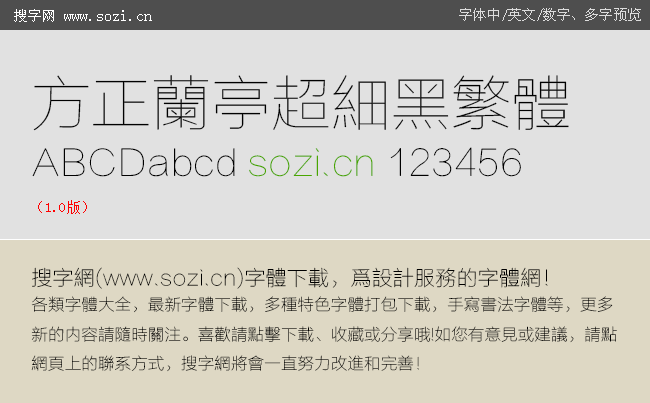
方正蘭亭超細(xì)黑繁體(FZLTCXHFW)
搜字網(wǎng)提供一款方正蘭亭超細(xì)黑繁體中文字體下載,方正蘭亭超細(xì)黑是一款線條非常細(xì)的中文簡(jiǎn)體漢字,該字體雖然纖細(xì),但結(jié)構(gòu)清晰,風(fēng)格統(tǒng)一,最主要效果非常好,能夠適用于廣告設(shè)計(jì)、名片設(shè)計(jì)、包裝印刷、產(chǎn)品設(shè)計(jì)等應(yīng)用,有喜歡的朋友可免費(fèi)下載收藏。